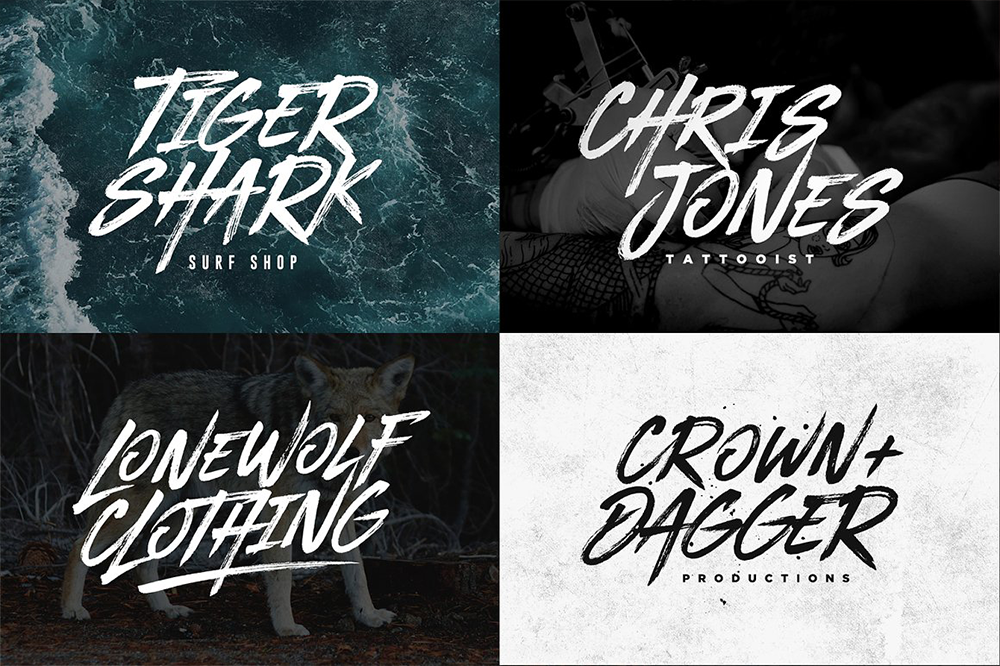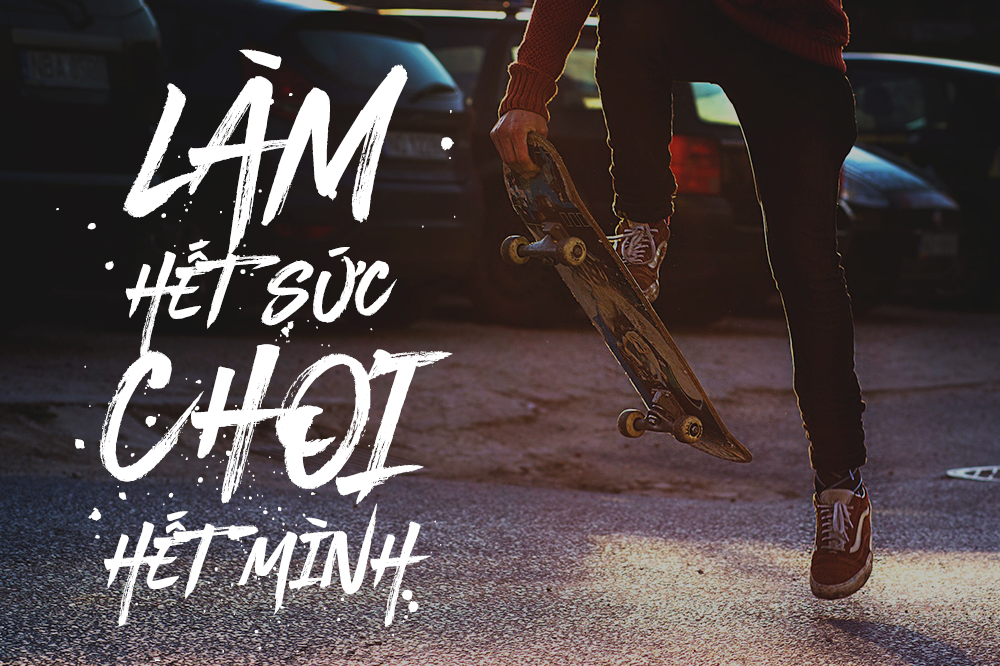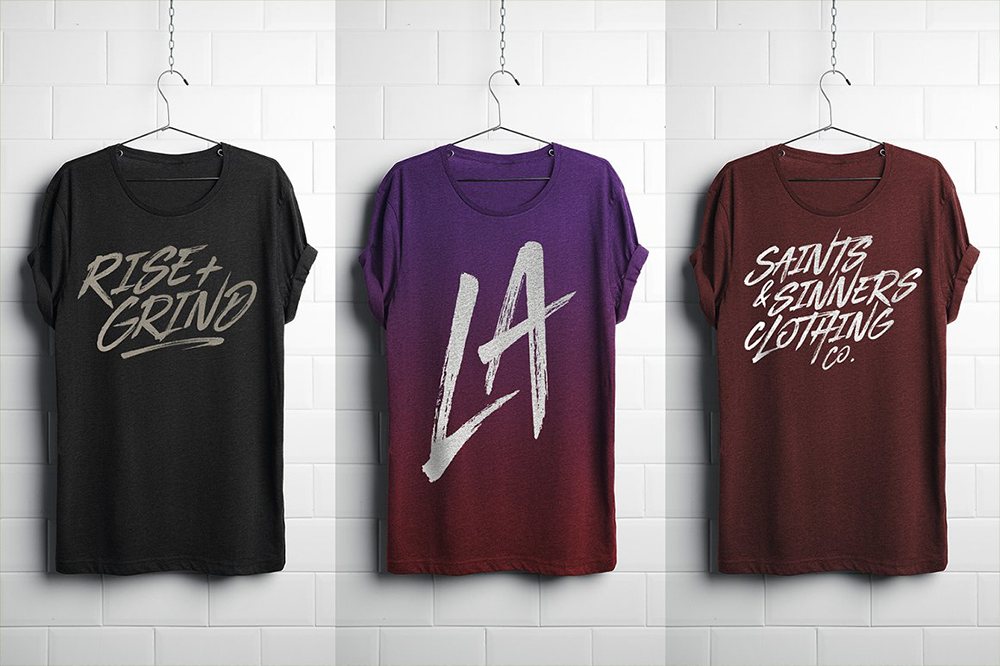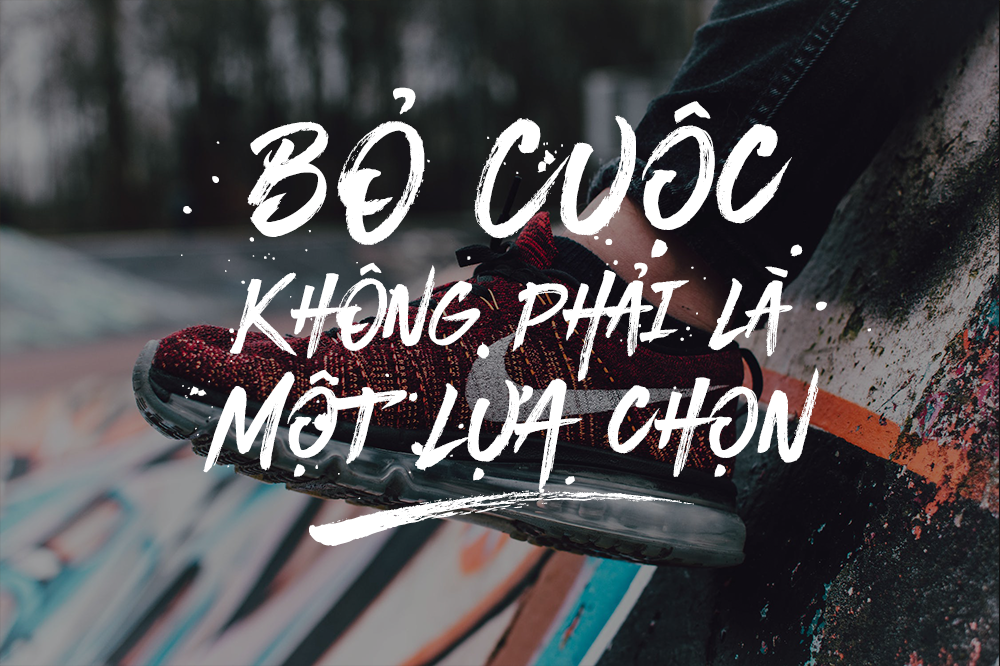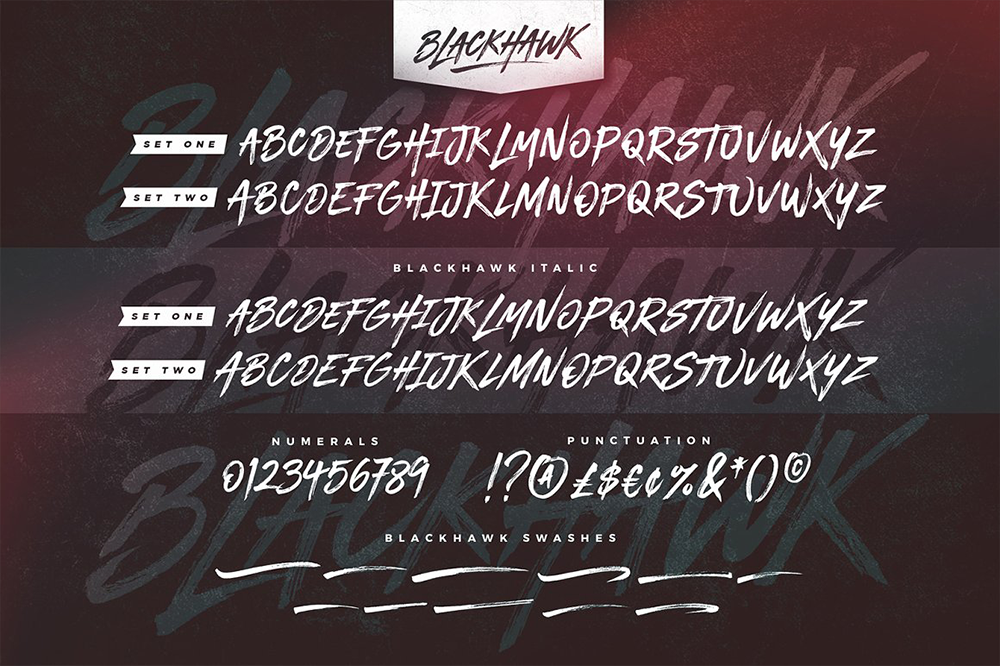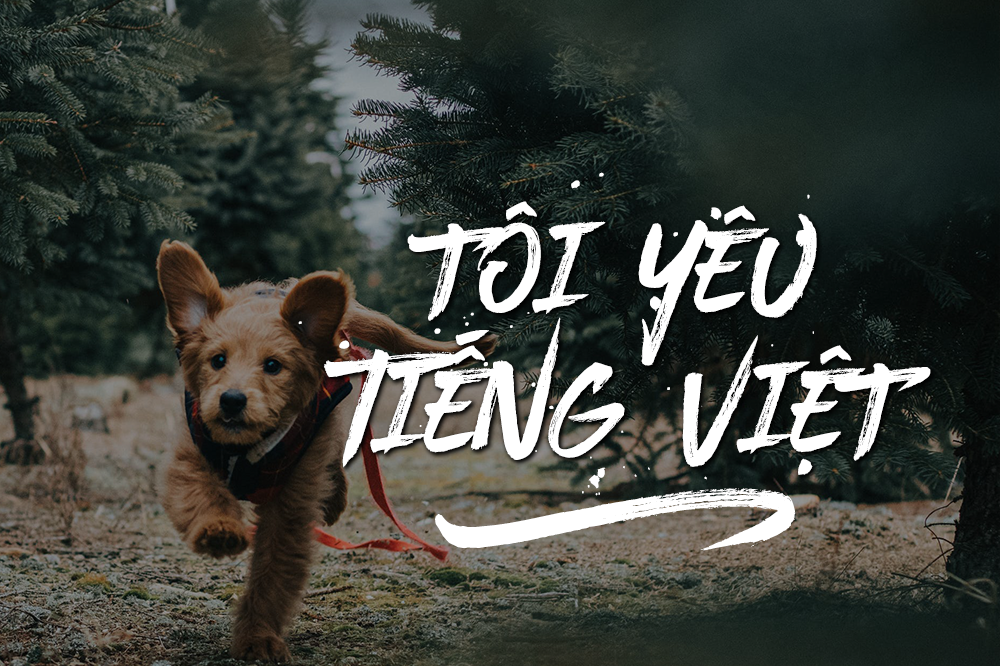
BLACKHAWK là một font chữ cọ mang phong cách đường phố đầy năng lượng và bùng nổ. Với sự chú trọng đặc biệt vào các nét vẽ nhanh và chi tiết sắc nét, BLACKHAWK chắc chắn sẽ truyền tải thông điệp mạnh mẽ, táo bạo và dồn dập; rất lý tưởng cho logo, thiết kế trang phục, trích dẫn, bao bì sản phẩm hoặc bất kỳ ấn phẩm nào cần một cú “tăng tốc” về mặt kiểu chữ.
Nhà thiết kế: Sam Parrett
Nhà phát hành: Set Sail Studios